【ポモドーロ/study with me 用】50分+10分 クロマキータイマーセット(手書き風フォント)
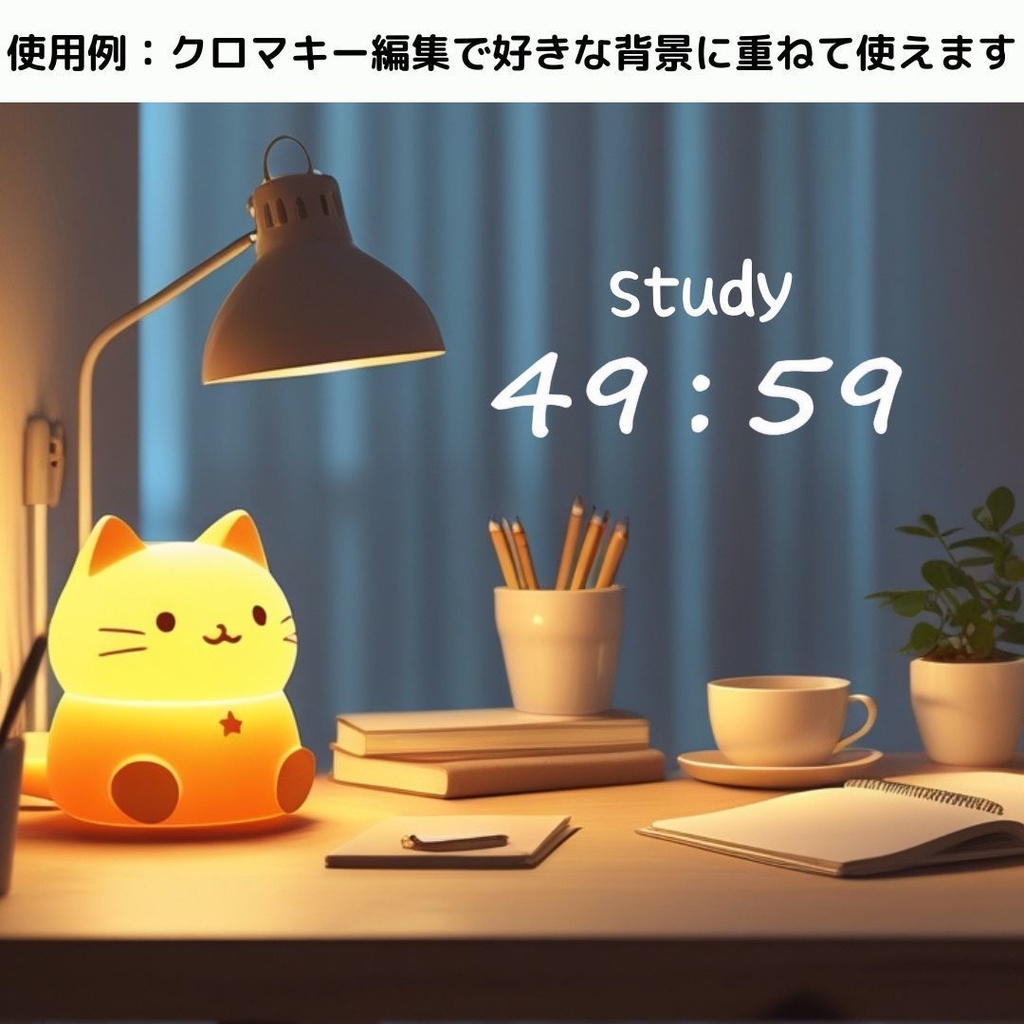
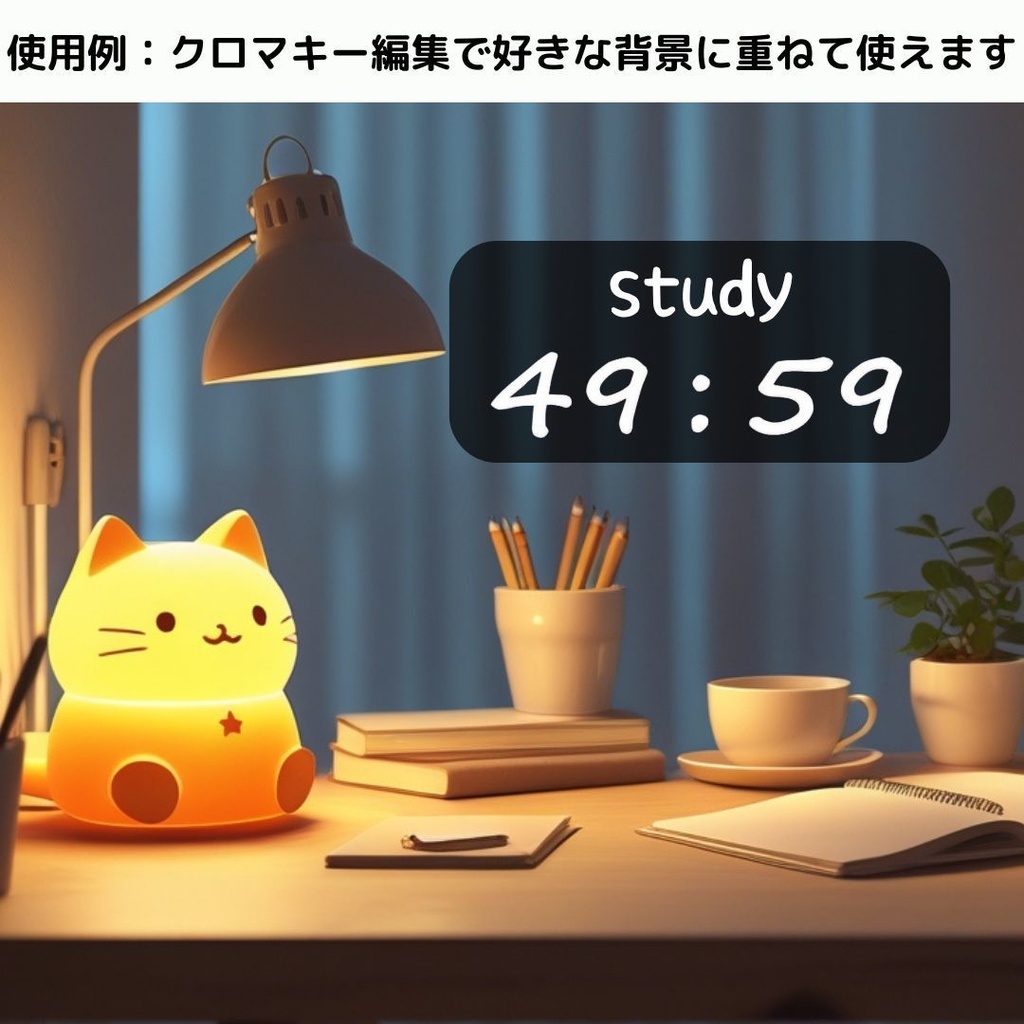
🎓 ポモドーロテクニックに最適! 勉強・作業・集中タイムに使える、50分+10分のクロマキータイマー素材セットです。 ✏️ 「STUDY WITH ME」や「作業用BGM動画」などにおすすめ! おしゃれな手書き風 Segoe Scriptフォント を使用。 🕒 セット内容: ・50分カウントダウンタイマー(49:59→00:00) ・10分カウントダウンタイマー(09:59→00:00) 🟢 クロマキー(グリーン背景)合成対応 🎞 商用利用OK(YouTube・SNS等で使用可) ❌ 再配布・再販売はNGです 🔽 ファイル形式:MP4(各1本ずつ) 🔽 解像度:1920×1080(フルHD) 🔔 ポモドーロ用ループ動画を作りたい方にもおすすめ! タイマーを繋げて「50分作業→10分休憩」の流れが簡単に作れます。 💡 動画編集初心者さんも安心! CapCut、Filmora、Premiere Proなど主要ソフトでそのまま使えるMP4形式です。